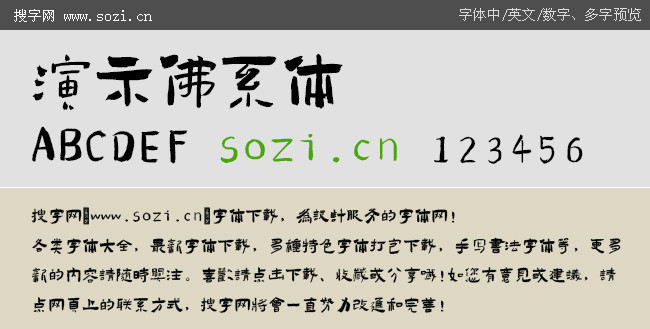
演示佛系體
搜字網(wǎng)給大家提供一款演示佛系體中文字體下載,本字體作者為紀(jì)國(guó)才老先生,出生于 1939 年的紀(jì)老先生一生酷愛書法,在80歲這年親手寫了一套獨(dú)具風(fēng)格的字體,本字體打破固有造字框架的條條框框,又有一致的內(nèi)核,形散而神不散;不再是常規(guī)書法字體中怒放的飛白和筆觸,將瀟灑收斂,但也厚重有力;且面向全社會(huì)發(fā)布,全渠道免費(fèi)商用!